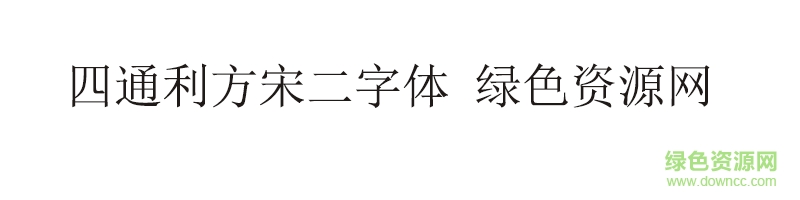
四通利方宋二字體是一款非常有個(gè)性的電腦字體軟件,字體簡(jiǎn)單大方行云流水,整體效果端正辨識(shí)直觀,使用起來(lái)風(fēng)格多樣簡(jiǎn)單實(shí)在??靵?lái)綠色資源網(wǎng)下載體驗(yàn)吧!
四通利方宋二字體是比較細(xì)的宋體字體,筆畫簡(jiǎn)潔大方;字形結(jié)構(gòu)端正,適用于包裝印刷、廣告設(shè)計(jì)、平面設(shè)計(jì)、書籍報(bào)紙等領(lǐng)域。